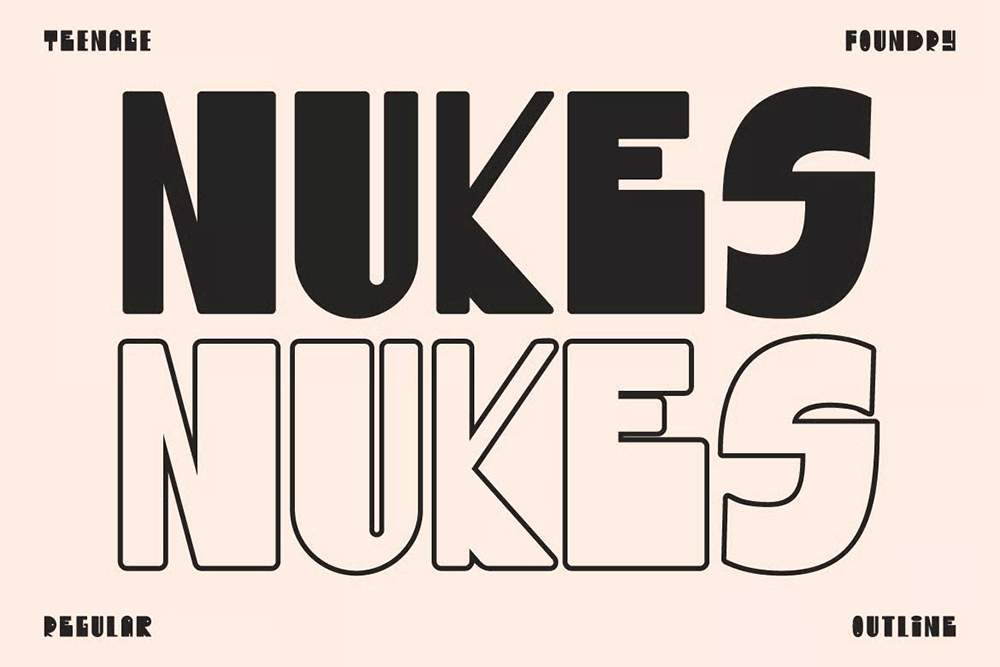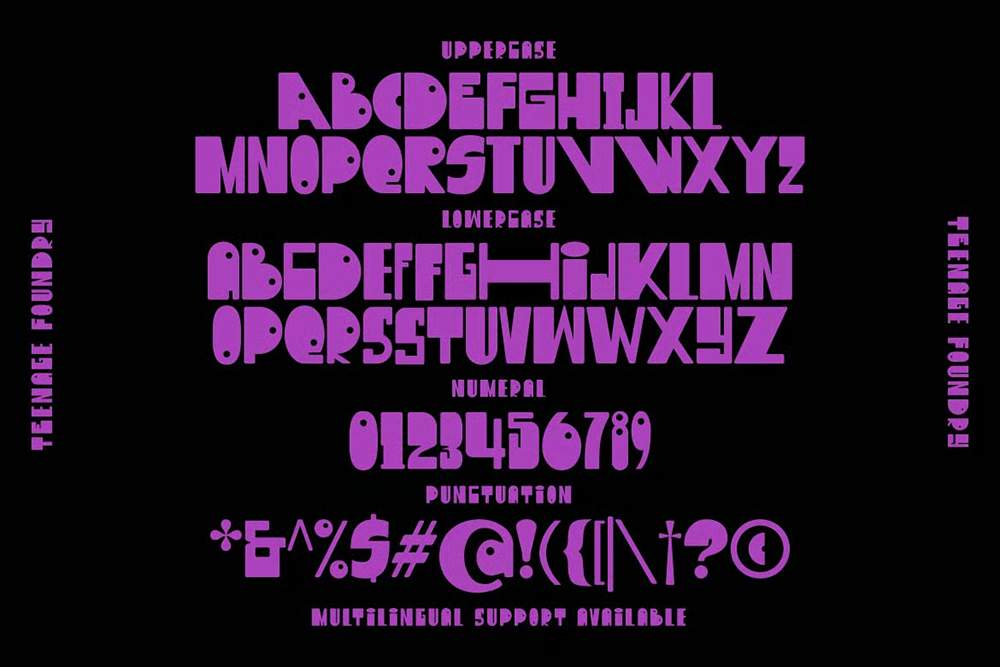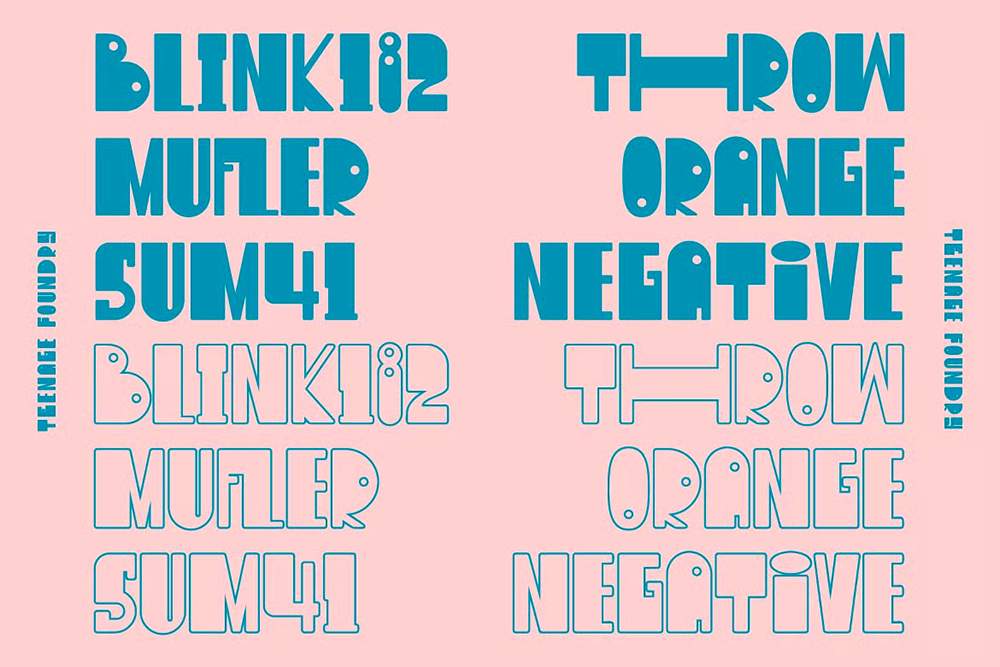
دانلود فونت انگلیسی TF Nukes Font
فونت پرمیوم و انگلیسی TF Nukes Font جسورانهترين فونت نمايشی که توجه مخاطبان شما را جلب میکند و پيام شما را برجسته میکند! اين فونت قوی و جسورانه برای عناوين، سرتيترها و هر متن ديگری که نياز به بيان چيزی دارد، عالی است.
مزایای استفاده از فونت لاتین TF Nukes چیست؟